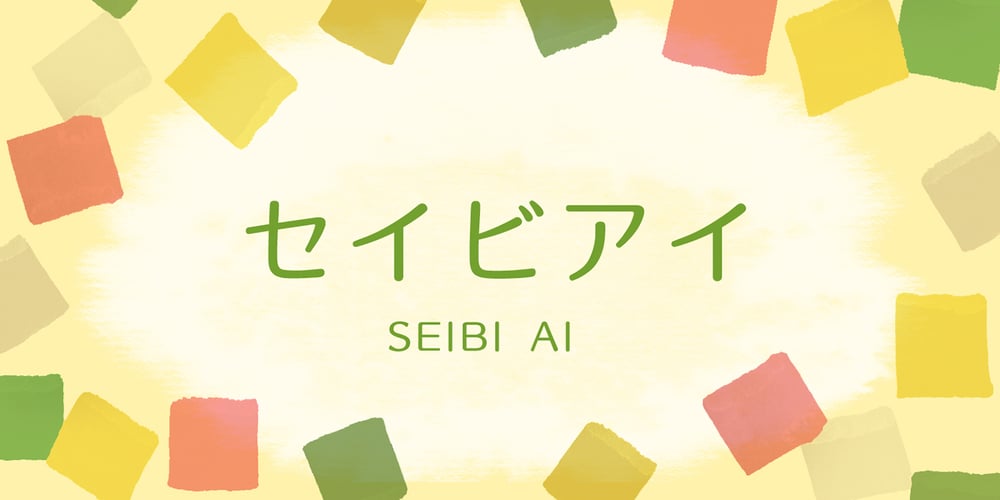
Seibi Ai Font Family was designed by published by Nihon Literal. Seibi Ai contains 2 styles and family package options. This typeface combines the rhythmic movement of Mincho and the simplicity of Gothic, with a rounded finish for a touch of elegance and style. 明朝のリズム感とゴシックのシンプルさに加え、ラウンド処理することでエレガントでおしゃれなイメージを求めた書体です。タテ画は太く、ヨコ方向はそれより細く、ハネなどはさらに細く、という三段階処理が施されています。昭和50 年(1975 年)頃、レタリング文字として開発。その後デザイン調整を経てフォント化されました。